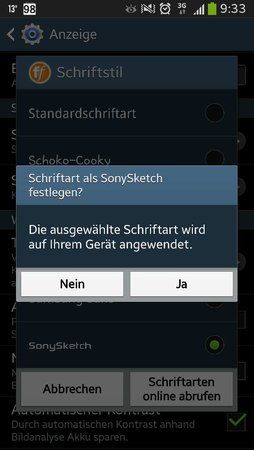
Schriftart (~Font) ändern
Wie das Thema schon sagt, würde ich gerne die Schriftart bei meinem Razr i verändern... Möglichst ohne root. Wie es z.B beim Samsung Galaxy von Haus aus geht. Hab hier im Forum nichts gescheites gefunden. Wäre dankbar für Tips!
Mit dem Lightning Launcher geht das z. B. Der Stock-Launcher hat leider keine solche Einstellungsmöglichkeit ohne ins System eingreifen (root) zu müssen.
leider habe ich ein Probelm mit meinem neuen S4.
Die Schriftarten lassen sich nicht richtig ändern - nur in bereits vorhandene Schriften.
Ich habe bereits verschiedene aus dem PlayStore geladen, diese werden auch angezeigt, aber ich kann sie nicht auswählen.
Wenn ich eine heruntergeladene auswählen möchte, zeigt das Gerät die Meldung: Diese Schriftart ist nicht verfügbar.
Gibt es für dieses Problem eine schnelle Lösung?
Als ich hab bei mir sonysketch.apk installiert und es lässt sich ohne Probleme (kein Root) umstellen.
Das hab ich auch schon drauf -.- .... geht auch nich. Ich bin voll am verzweifeln und mitlerweile echt genervt!
Sonysketch habe ich auch installiert (die selbe .apk wie auf dem S2). In der AUswahl erscheint die Schrift auch, nur kann ich sie auch nicht auswählen.
Menno, die will einfach nicht.
Bild 1 bestätigen, dann kommt sofort Bild 2
Ich habe das gleiche Problem
Ebenfalls diese Fehlermeldung,MDM und gerootet.
Komsiche Sache. Ich hatte sie unter MDE isntalliert -> OTA update auf MDM gemacht -> Schriftart wurde übernommen. Jetzt hab ich mal wieder die Standardschrift eingestellt und wollte zurück auf die Sonysketch Schrift. Keine Chance. Es kommt immer die o.g. Meldung. Scheint mMn am Update gelegen zu haben.
Viele gingen bei mir auch nicht, aber die kostenpflichtige Bauhaus FlipFont lief beispielsweise problemlos. Möglich ist es also schön, aber es scheint als wenn sich etwas an der Prozedur geändert hat und viele im Store damit noch nicht kompatibel sind.
habt ihr eine Ahnung wie man an die Heletica S vom S2 mit ICS kommt? Die Standartschriftart ist das doch nicht beim S4? Und Samsung Sans ist irgendwie runder. Zum lesen von Internet war Helvetica von den auf S2 installierten hier besser. Oder täuscht es durch die andere Auflösung?
Habe auch probiert Schriften vom S2 zu übernehmen(von Font manager und Carb...Helium gesichert). Klappt auch nicht. Auch Neustart half nicht.
"Schriftart ist nicht vorhanden"
Wenn jemand Helvetica S zum laufen bringt bitte posten.
Hmmm...hatte ja versucht die Schrift von Rob zu installieren.Aber nachdem ich die apk dann wieder entfernt hab(weils ja net funzt),stehen die anderen Schriftarten jetzt auch nicht mehr zur Auswahl,hmpf...installiert sind sie aber...hat das noch jemand?
Edit:Warum auch immer...die vorinstallierten Schriften sind nun wieder da :D
habe gerade zumindest die Helvetica wieder gefunden als apk. die funktioniert wenn man die installiert. (auch mit mdm)
Die Erkenntnis...wenns bei einer geht dann gehts auch bei anderen Schriften